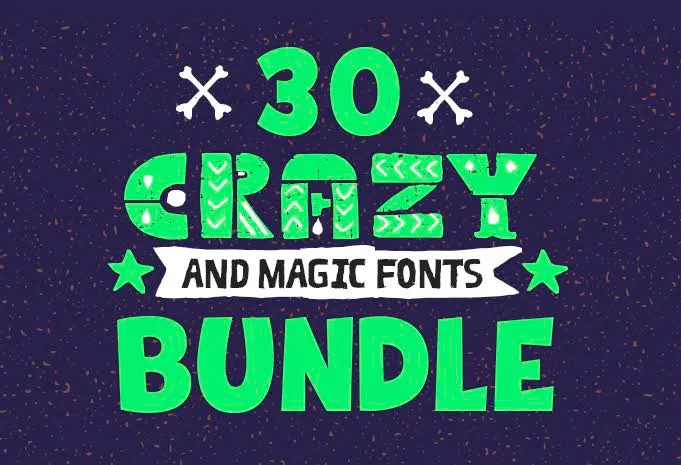
30 Crazy Fonts By Rodrigo
Коллекция из 30 акцидентных шрифтов для создания ярких визуальных акцентов в дизайне. Набор включает разнообразные начертания, ориентированные на привлечение внимания в заголовках, плакатах, обложках и рекламных креативах. Шрифты подходят для проектов, требующих выразительной типографики и необычной подачи текста.
- 30 авторских шрифтов в различных стилях